展覧会「秀英体100」のおしらせ(2011/9/15更新)
designed by Kazumasa Nagai
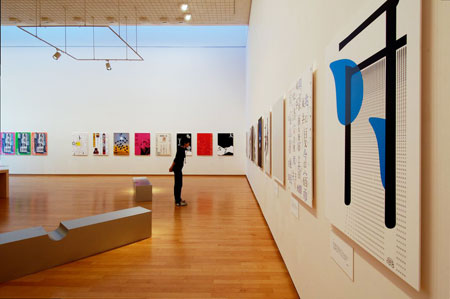
CCGAでの展示の様子
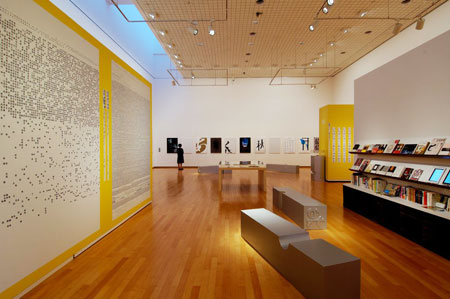
CCGAでの展示の様子
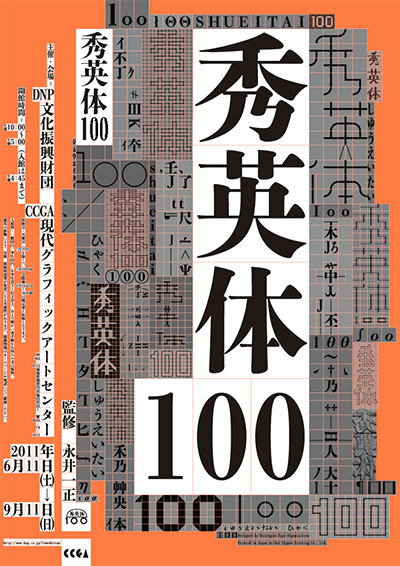
designed by Dainippon Type Organization
から大阪へ巡回した「秀英体100」、お待たせしました福島県須賀川市のCCGA現代グラフィックアートセンターへ巡回いたします。
最後の巡回展ということで、gggや大阪では登場しなかった作品を追加! 既にご覧になった方も、また見に来ないといけませんね!
CCGA現代グラフィックアートセンター 企画展「秀英体100」
監 修 永井一正
告知物・展示デザイン 大日本タイポ組合
いまから100年前の明治末期、秀英舎が開発した活字は完成期を迎えていました。明治36年、43年、大正3年と立て続けに総合見本帖を発行しただけでなく、各活字サイズ・書体ごとの全字種見本帖も発行され、秀英体が量・質ともに充分だったことがうかがえます。
活版印刷からDTP用のフォント、あるいは電子書籍や映像で使われるなど、100年の間に秀英体も大きく変化してきました。そして2009年11月を皮切りに、モリサワから一般販売が開始され、より多くの方々の手に秀英体が届く環境が整ってきました。
今回の企画展では、秀英体生誕100年を記念し、DNPが創業当時から引き継いできた秀英体という文化資産の魅力を、より広く一般の皆様に親しんでいただくことがねらいです。
秀英体の四季
24名+一組のグラフィックデザイナーによる「四季」をテーマに作成された新作ポスターを展示いたします。平成の大改刻で開発した秀英初号明朝、秀英明朝L/M/B、そして目下開発中の秀英角ゴシック&丸ゴシックを使ったポスターで、秀英体の新たな魅力をお伝えします。
浅葉克己・井上嗣也・葛西 薫・勝井三雄・佐藤晃一・佐野研二郎・澁谷克彦・杉浦康平・杉崎真之助・祖父江 慎・高橋善丸・立花文穂・永井一正・中島英樹・長嶋りかこ・仲條正義・中村至男・南部俊安・服部一成・原 研哉・平野敬子・平野甲賀・松永 真・三木 健 + コントラプンクト(デンマーク)
秀英体の100年
秀英体の誕生から平成の大改刻まで、秀英体の100年を書籍・雑誌・新聞広告・ポスター・電子書籍、さまざまなメディアや開発資料とともにご紹介いたします。
また、ワンパクによる、秀英体を使ったインタラクティブコンテンツ「写心機 ver.2」も登場します。